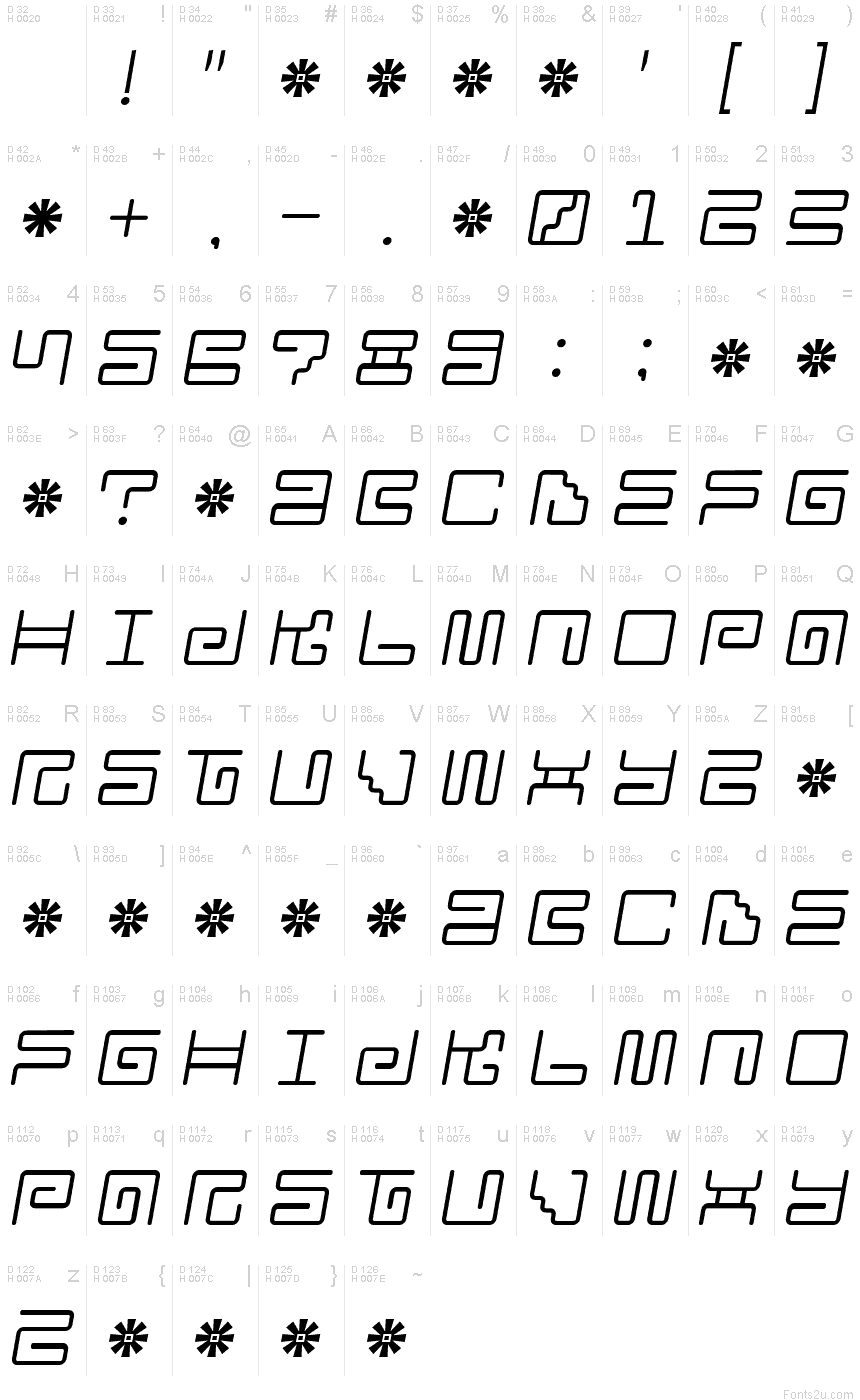
Iron Lounge 2
Iron Lounge 2 di Jakob Fischer è un carattere display futuristico gratuito, caratterizzato da un design monolinea elegante e angoli leggermente arrotondati. Ogni lettera presenta una sottile inclinazione in avanti, come se fosse in movimento ad alta velocità: questo conferisce a titoli e loghi un'energia sci-fi aerodinamica, senza risultare fredda o meccanica. Le curve generose e le controforme aperte garantiscono leggerezza e leggibilità, anche nelle dimensioni più grandi.
Con Iron Lounge 2 puoi dare un’identità coerente e high-tech a canali gaming, startup tecnologiche, team e-sport, poster synthwave o mockup di interfacce futuristiche. Questo font gratuito è perfetto anche per packaging, flyer di eventi e loghi d'impatto in cui cerchi dinamismo e modernità. Prova ad abbinarlo a un carattere sans serif geometrico pulito per il testo, lasciando che Iron Lounge 2 si occupi dei titoli e dei loghi per far risaltare davvero tutta la sua velocità.